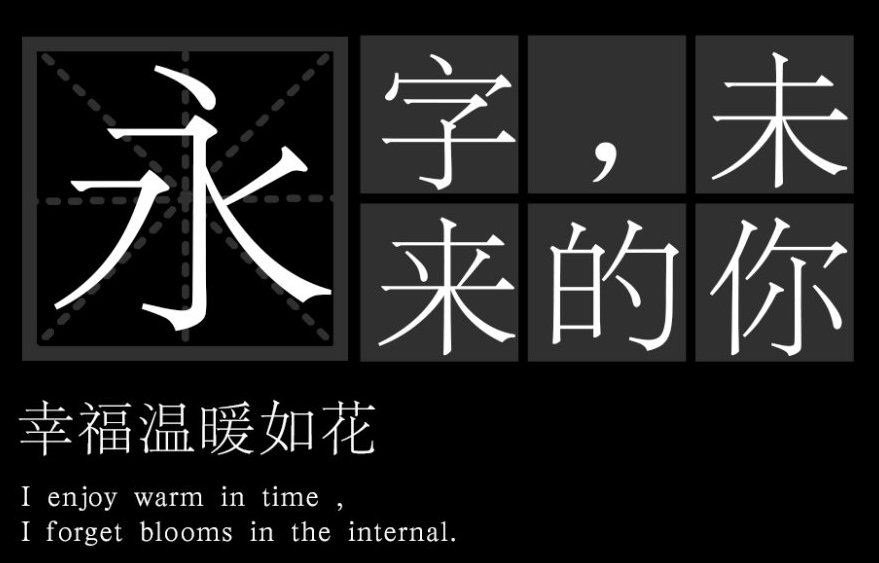
“印研所宋一体”,延续了宋体一贯的风格特征,拥有洋气的笔触,高雅显格调。具有较强的感情色彩,如历史感、秀气、文质彬彬等气质,富有深厚的文化底蕴。图片字体 在笔画上,仍然保持了中国书法的本质特征。在与唐楷颜体比较时,我们看得更清楚,如点、捺、撇及转折处的顿挫处理,就是对书法运笔进行了高度的艺术化概括。
今天版本学家们对于宋体字下的定义是:“横平竖直,横细竖粗,起落笔有棱有角,字形方正,笔画硬挺。”起落笔的棱角,应是 宋体字的最大的特征。为了多方面的需求,设计师们在保留传统宋体字的基础上融入了新时代的许多创意,现在宋体字增添了了多种诠释。
这款字体创作灵感源于上海印刷技术研究所1962年完成的专为排印新中国首部《辞海》正文设计的“宋体一号”原稿。加入新的创意后,字形方正,笔形清秀;结构严谨,黑白匀称;精致典雅,款整齐,阅读流畅特别适合大型工具书时尚行业、奢侈品、女性行业使用。